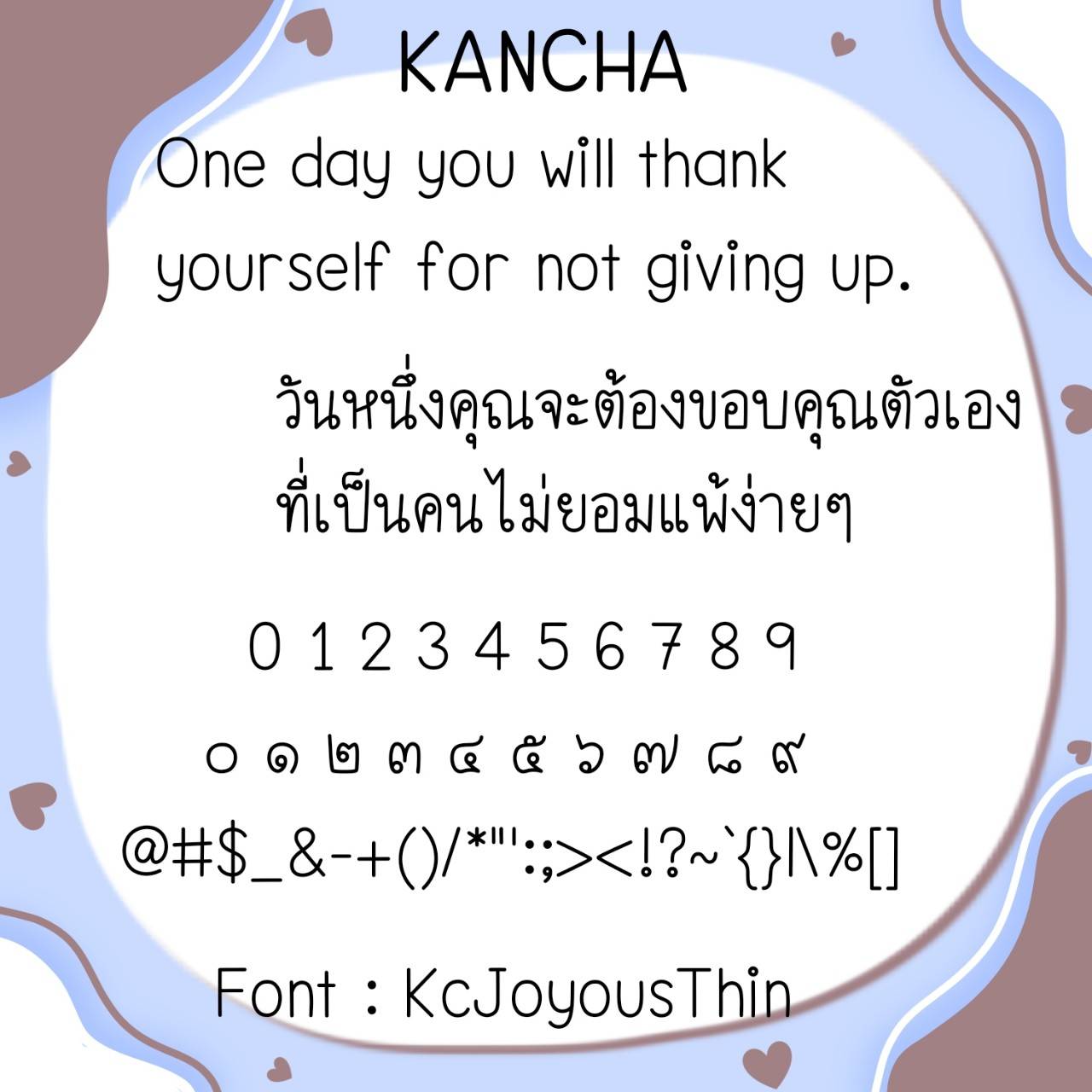
Font KcJoyous
🔸ฟอนต์แนวน่ารัก อ่านง่าย มีอิโมจิมิกกี้เมาส์แทนเลขไทยมาให้ด้วยค่ะ 🥰💙
🔹Cute, easy-to-read fonts with Mickey Mouse emojis instead of Thai numbers.🥰💙